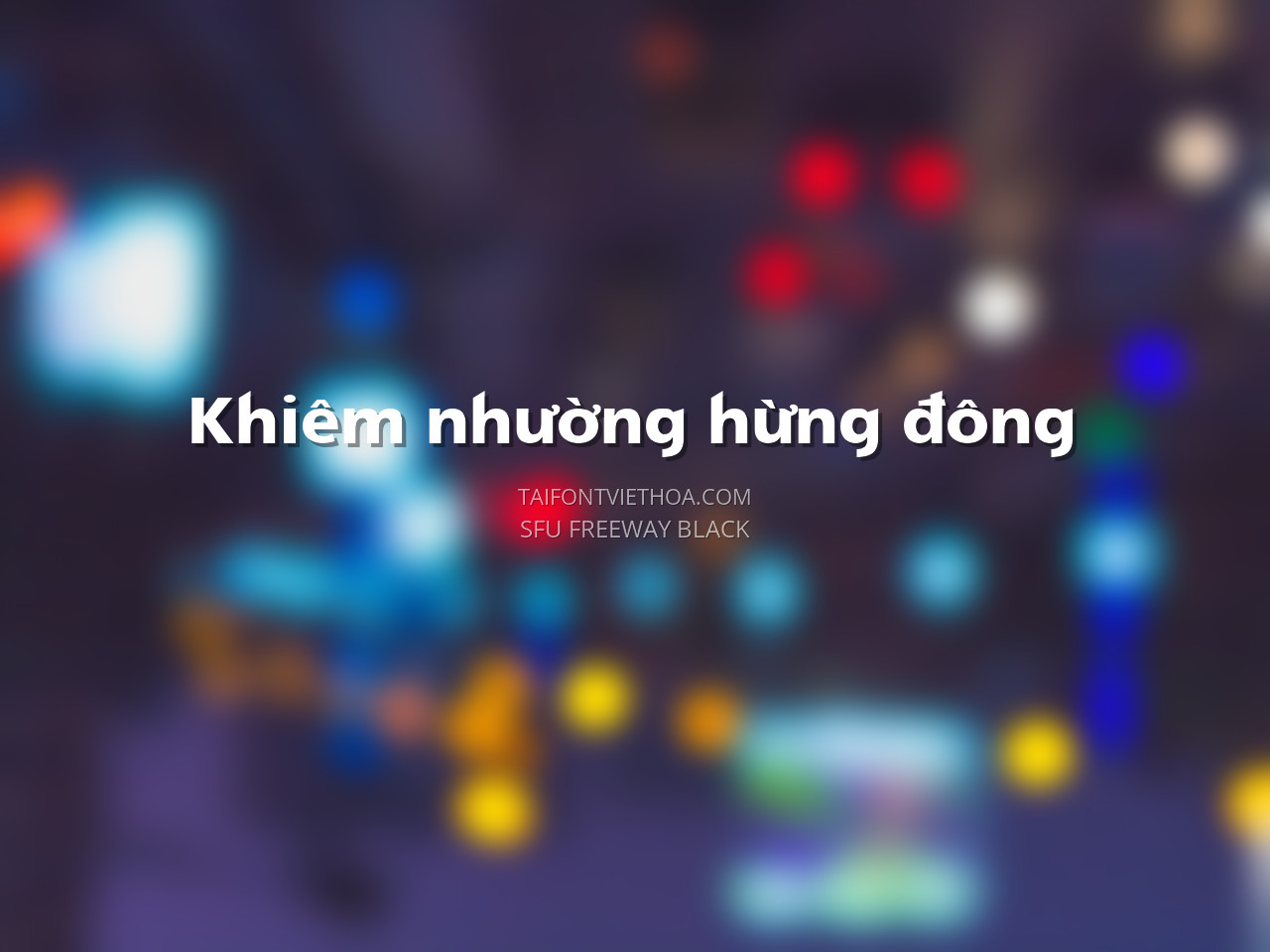
Font việt hóa SFU Freeway
Giới thiệu về font SFU Freeway – Kiểu chữ sans-serif đậm chất giao thông hiện đại
SFU Freeway là phiên bản Việt hóa của font Freeway – một kiểu chữ sans-serif lấy cảm hứng từ bảng chỉ dẫn giao thông và biển hiệu đường cao tốc. Với thiết kế đơn giản, dễ đọc và trực diện, Freeway mang lại cảm giác mạnh mẽ, rõ ràng và hiệu quả trong truyền đạt thông tin. Font thường được sử dụng trong các thiết kế cần tạo ấn tượng nhanh, dễ nhận biết ở khoảng cách xa hoặc trên các nền tảng truyền thông công cộng.
Phiên bản SFU Freeway được Việt hóa đầy đủ, hỗ trợ tiếng Việt với dấu và ký tự đặc biệt trọn bộ. Taifontviethoa.comđã chọn lọc và giới thiệu font này như một công cụ hữu ích cho nhà thiết kế Việt khi cần xử lý các dự án đòi hỏi tính hiệu quả cao về mặt thị giác và tốc độ nhận diện thương hiệu.
Thiết kế dứt khoát, dễ nhìn và tính ứng dụng thực tiễn cao của SFU Freeway
SFU Freeway sở hữu cấu trúc sans-serif cứng cáp, các đường nét vuông vức, khoảng cách chữ cân bằng và độ dày đều, tạo cảm giác ổn định và mạnh mẽ. Các ký tự có hình dáng đơn giản, không cầu kỳ, nhằm tối ưu hóa khả năng đọc nhanh trong các tình huống cần phản xạ tức thì – như giao thông, chỉ dẫn, hay cảnh báo.
Ứng dụng lý tưởng: biển hiệu, banner quảng cáo, chỉ dẫn công cộng, thiết kế công nghiệp, bảng tên doanh nghiệp, các ấn phẩm marketing ngoài trời và giao diện thiết bị kỹ thuật. Ngành nghề phù hợp: giao thông vận tải, xây dựng, logistics, công nghệ, sản xuất, bất động sản, thương hiệu công nghiệp và các lĩnh vực cần sự trực quan và rõ ràng.